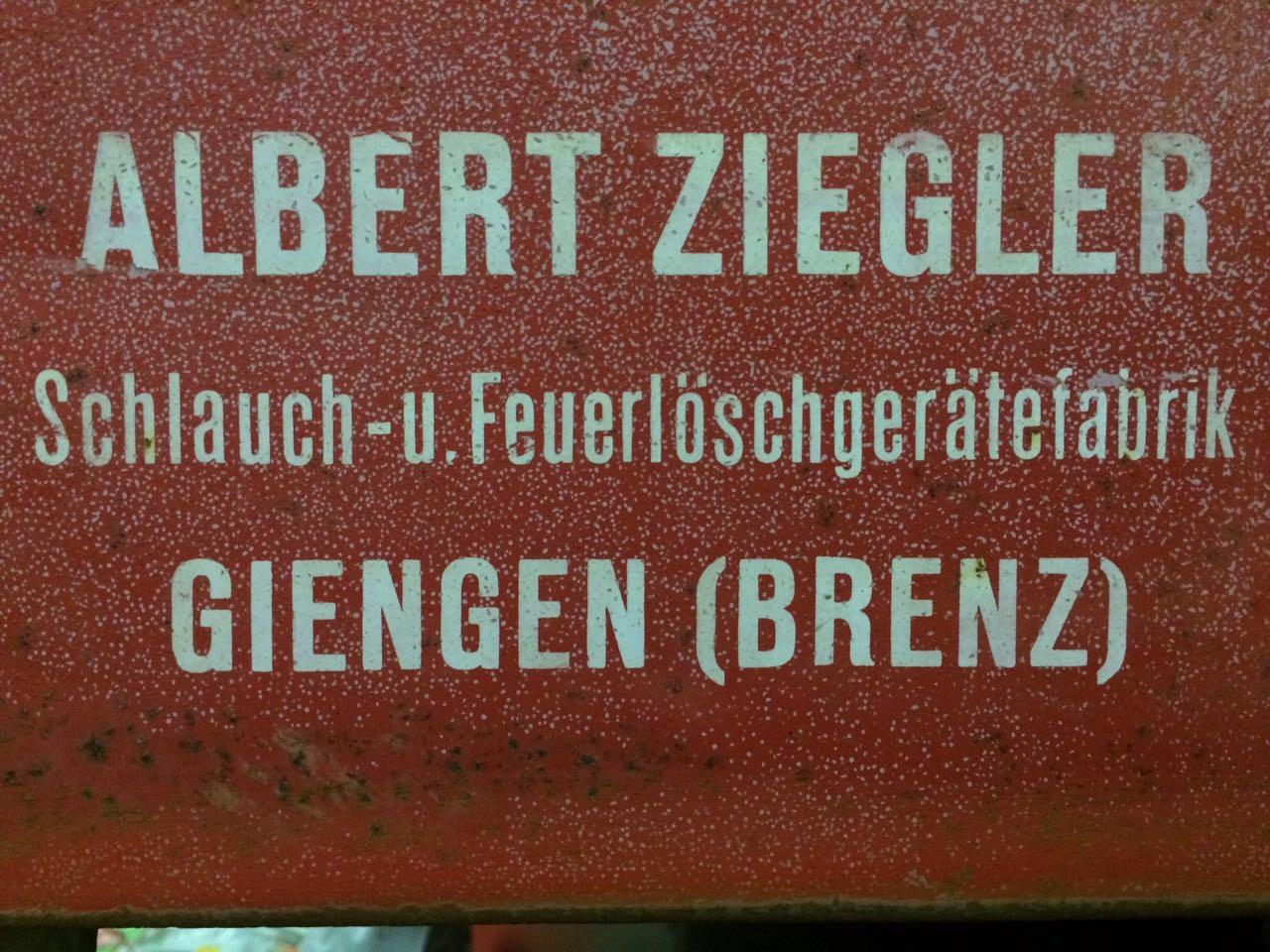
Suche Schriftart der Firma "Albert Ziegler"
ich suche die Schriftart auf dem angehängten Foto. Das Foto zeigt den Schriftzug auf einem alten Feuerwehranhänger der Firma Ziegler.
Leider komme ich bei meiner Suche im Netz nicht weiter. Markant sind vielleicht die leicht runden Klammern bei "Benz"!?!